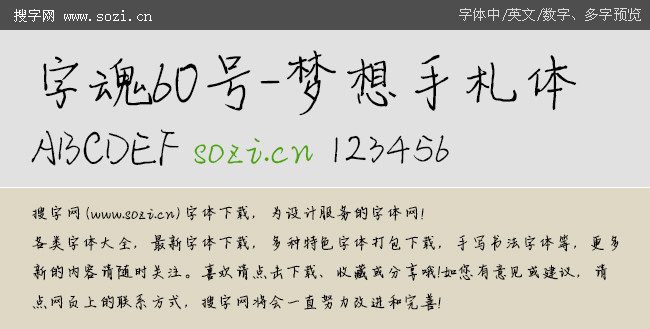
字魂60號(hào)-夢(mèng)想手札體
搜字網(wǎng)提供一款字魂60號(hào)-夢(mèng)想手札體中文字體下載,該字體是一款硬筆手寫字體,該字體包含6763個(gè)中文、字母、 符號(hào)和數(shù)字,具有創(chuàng)意、復(fù)古、古典、簡(jiǎn)約 的風(fēng)格,可以滿足您設(shè)計(jì)上的各種需求,該字體主要用于廣告、影視傳媒、青春校園、活動(dòng)展會(huì)、雜志、圖書、H5、活動(dòng) 等場(chǎng)景。